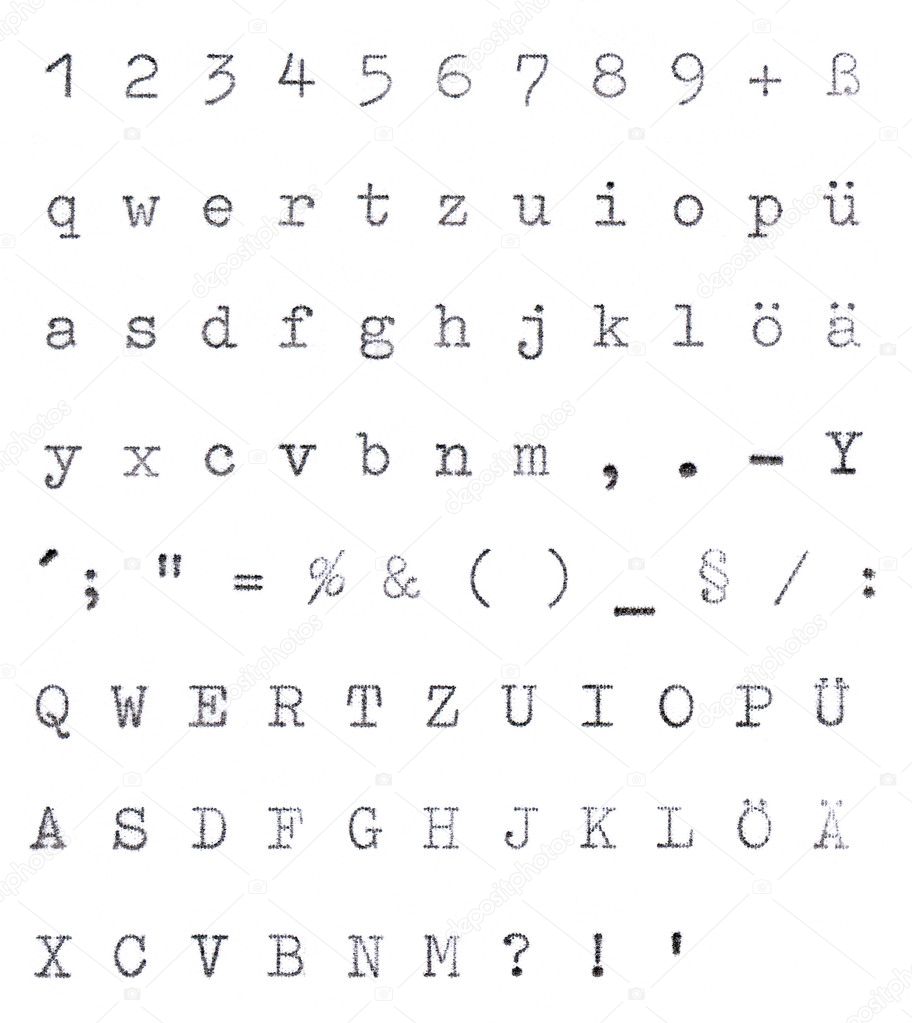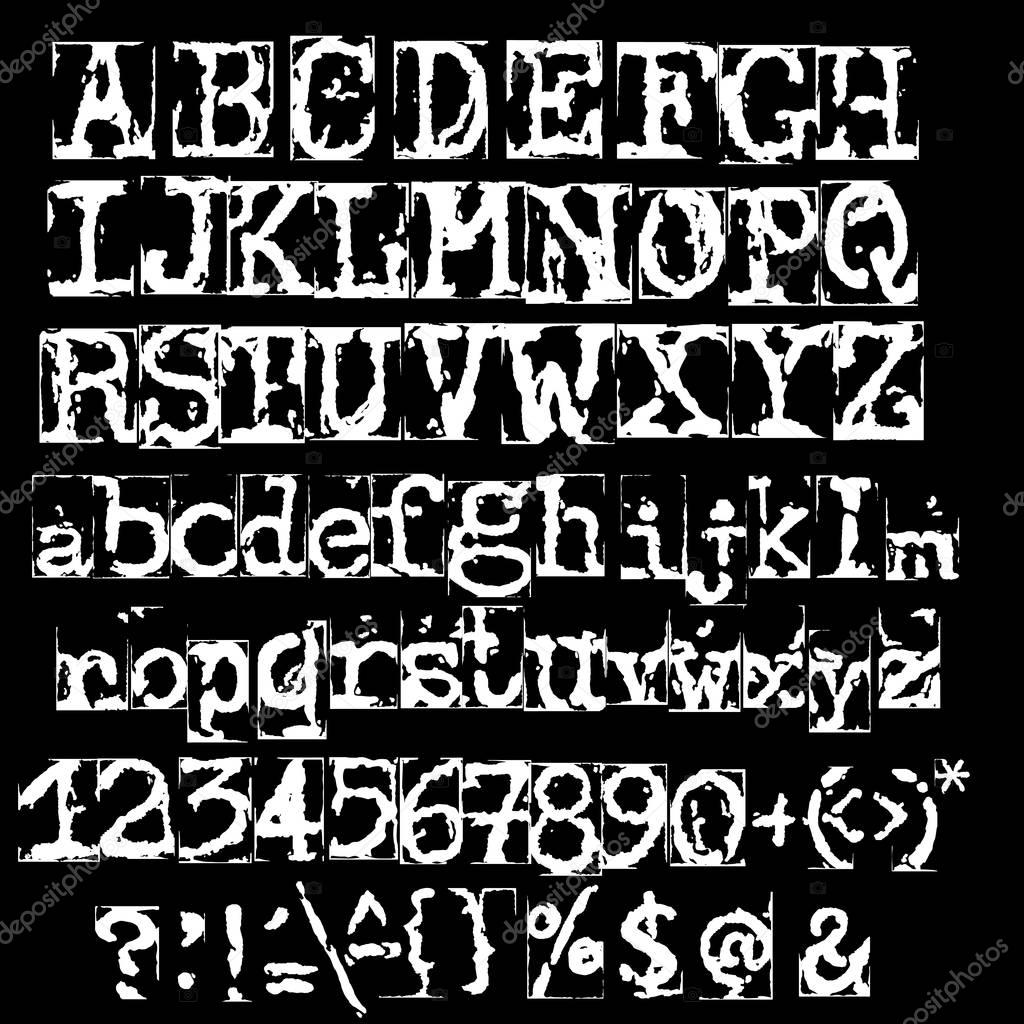
Кириллица печатная машинка шрифт
шрифт как печатная машинка Машинописный кириллический шрифт B52. Скачать машинописный шрифт B52 (кириллица и латиница).
Обалденный шрифт! Кстати, если кому не лень, посмотрите на сайте майкрософт офис шаблон оформления печатная машинка.
Символы шрифта печатной машинки немного смазаны и расплывчаты. красивые газетные, печатные и типографские шрифты на кириллице.
Неплохая имитация текста, напечатанного машинкой, у которой почти высохла красящая лента. Скачать с .
B52. Пример написания с использованием шрифта печатной машинки B52. B52, b52, B-52, b-52. Я искал, я нашел. Шрифт B52. Фонт B52. Имитирует.
Пи́шущая маши́на (разг. прост. «печатная машинка») механический. Так , например, на портативных пишущих машинах с русской кириллицей количество. В основе компьютерных шрифтов семейства «Курьер» (Courier ).
FF Trixie Семейство: Печатная машинка. Мало что из этих шрифтов есть для кириллицы, поэтому эта подборка больше подойдет для.
Фильтра по языкам нет; поиск по слову «cyrillic». GNUTypewriter. Неплохая имитация шрифта печатной машинки. Этот шрифт не.
Из всего многообразия шрифтов с кириллицей прошлого года в. попросту лишено контраста и похоже на набор печатной машинки.